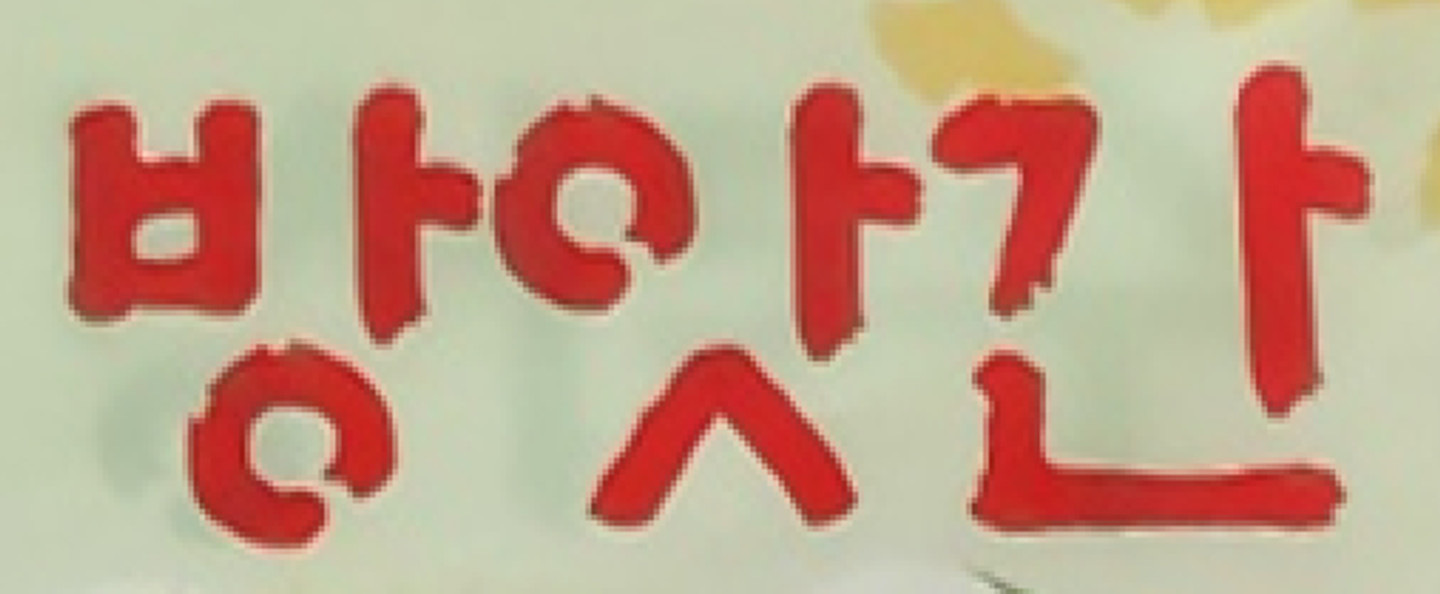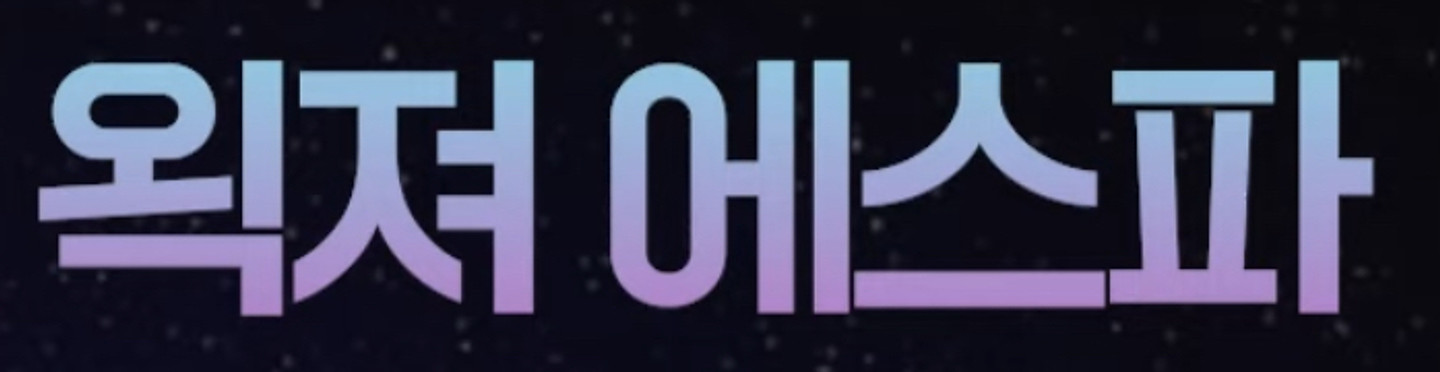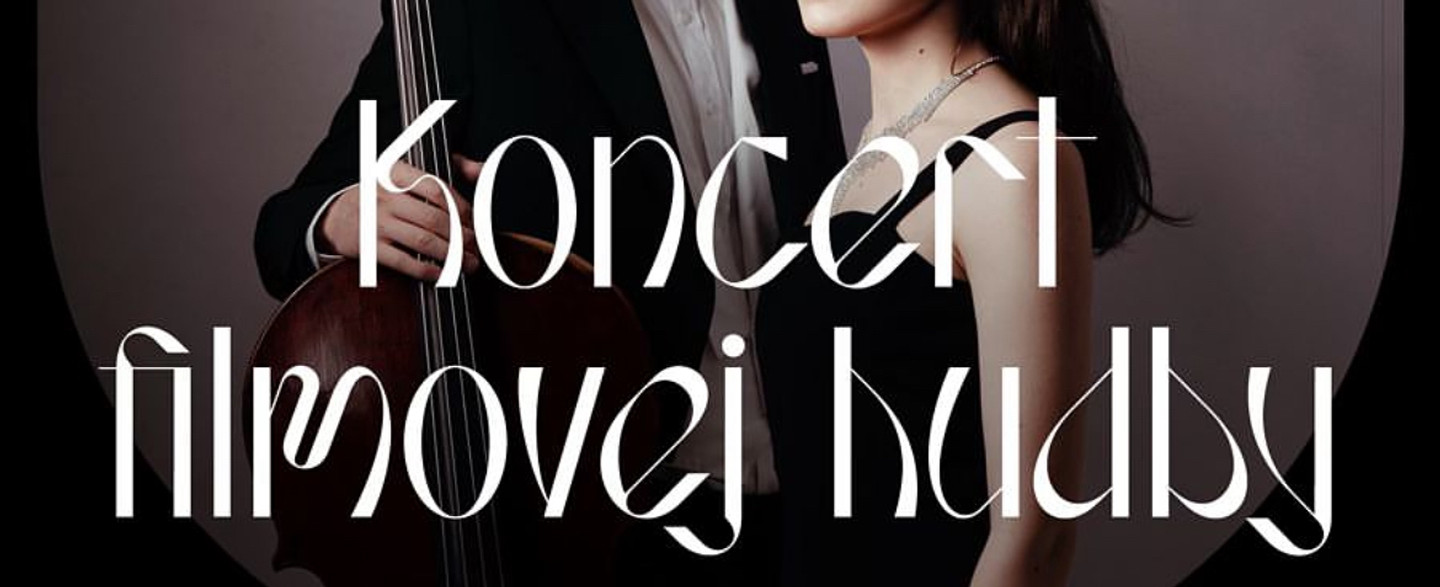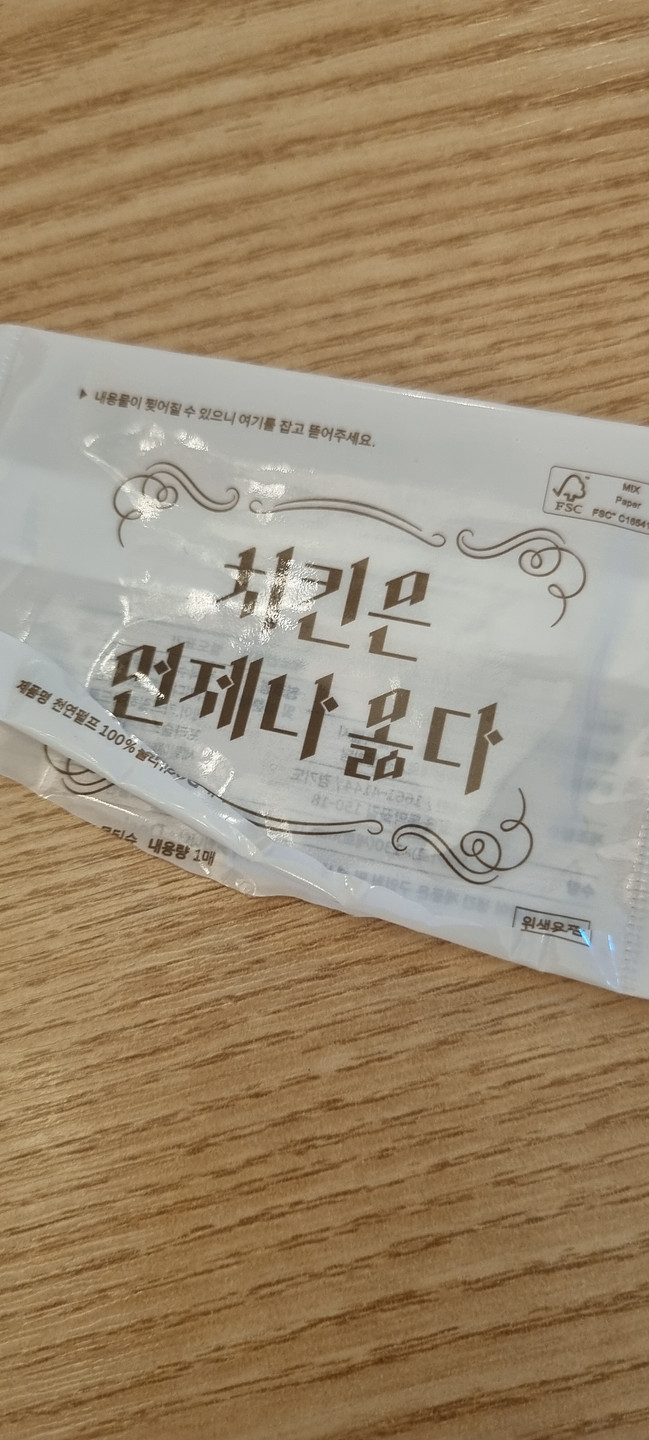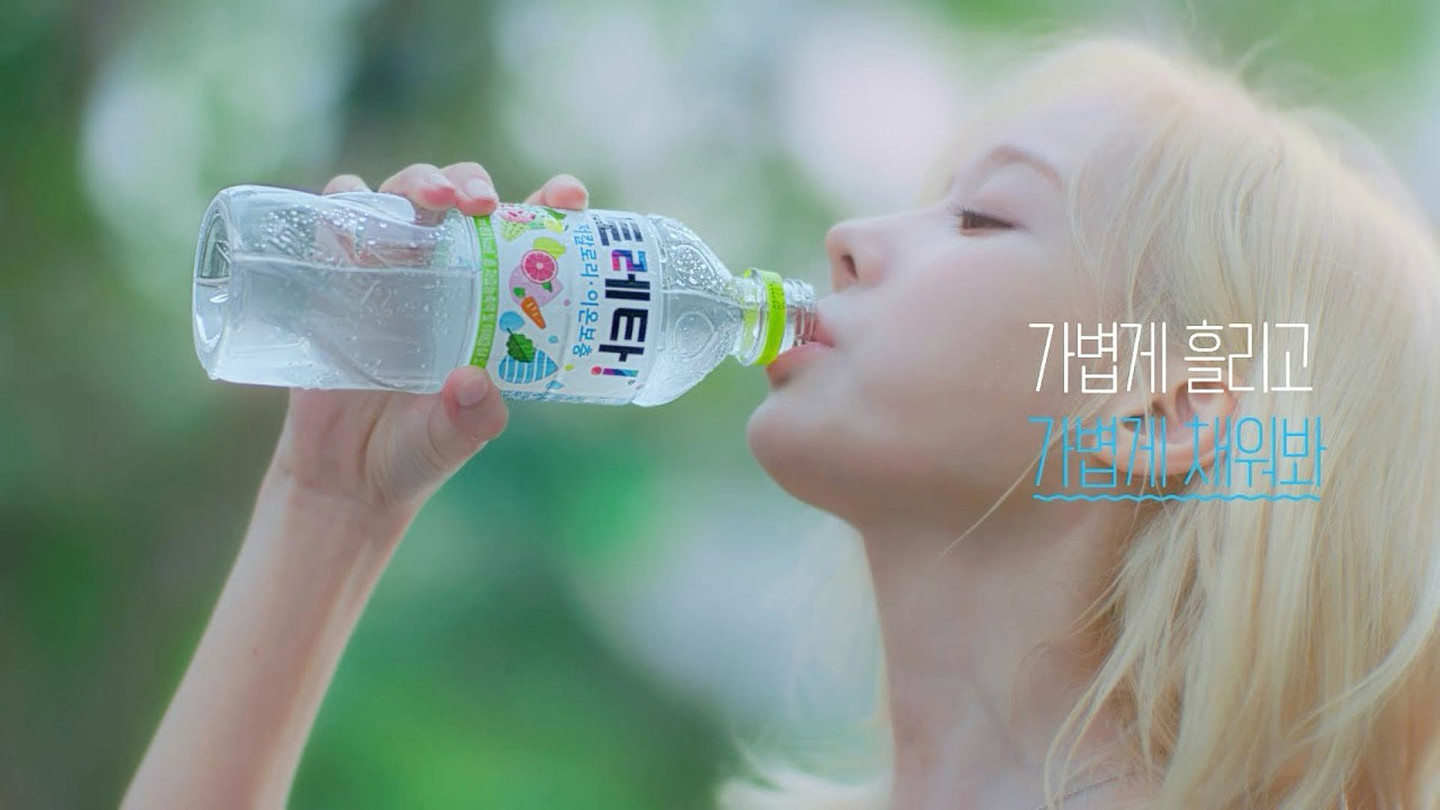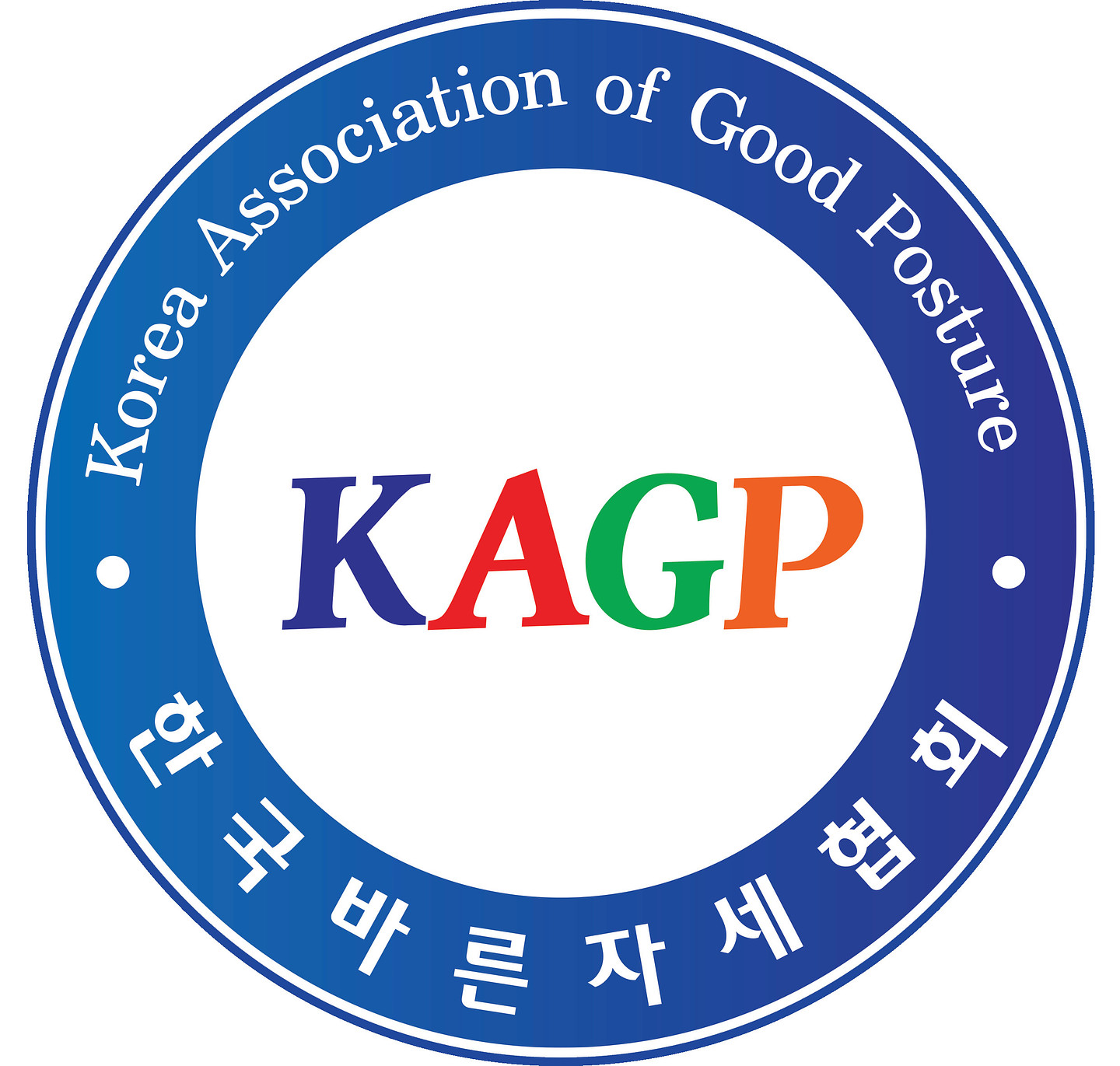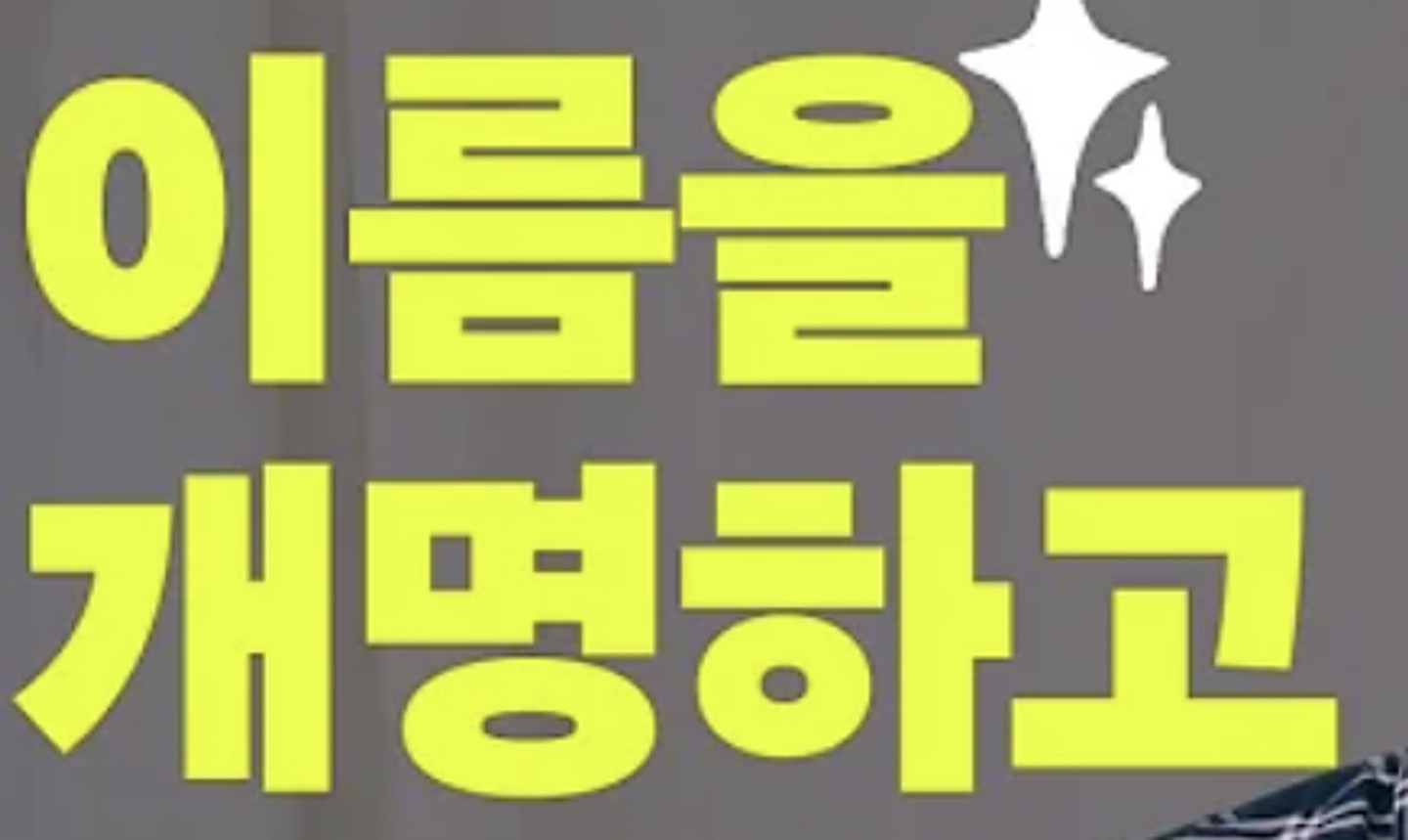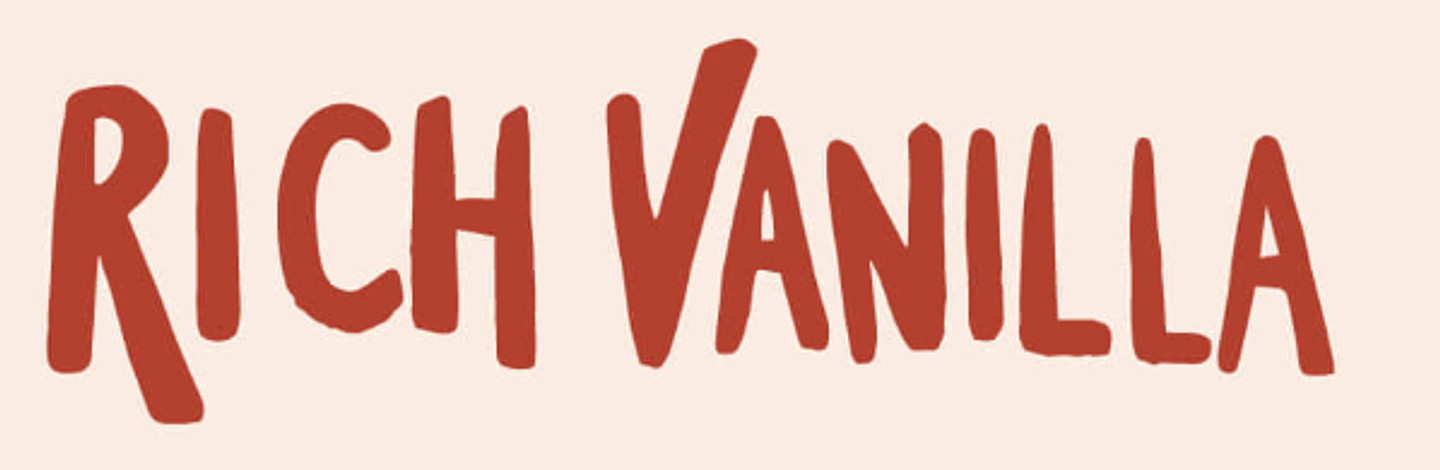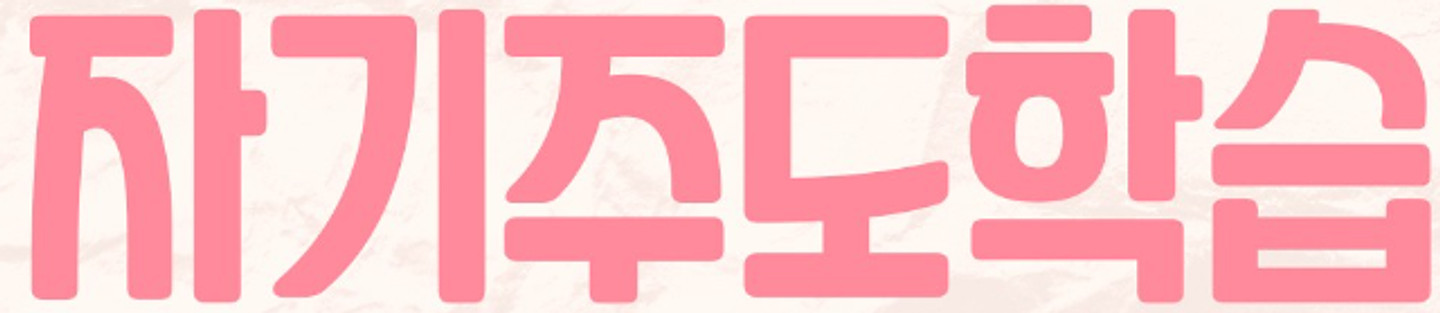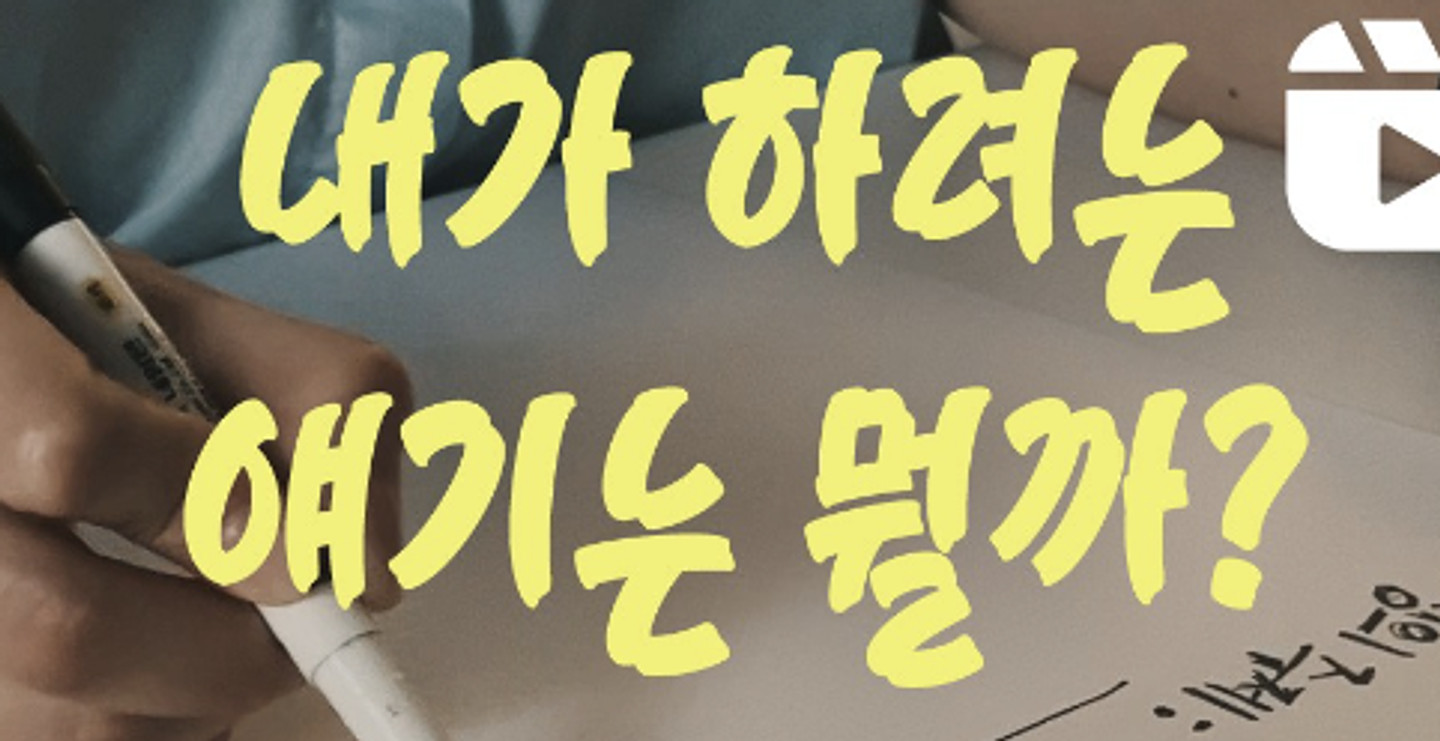
네. 오감을 자극하는 ~ 이 부분의 손글씨 같은 폰트 이름 알려주실 수 있을까요? 감사합니다.
타카슬라임카페 폰트명 부탁드립니다.
이거구 조금 왜곡잇습니다,,센세,, 찾아주십쇼ㅠㅜ
이 폰트좀 알려주세요
무슨 폰트인가요? ㅜㅜ 알고 싶습니다!!
무슨폰트인가여
예스24 티켓 뒷면 주의사항에 있느 글씨체 뭔가요?
'이제 c팀에서는' 글씨체 뭔가요?
이 폰트 아시는 분 계실까요? 알려주세요!
요 굴림이 어떤 폰트인지 궁금해요!!🤲 혹시 유료라면 비슷한 어도비/눈누에서 다운받을 수 잇는 폰트도 잇을까요🥺
이 썸네일 폰트 뭔가요?
<당연하게도 나는 너를> 폰트 질문합니다.
폰트 뭘까여
어떤 폰트인지 궁금해요!
폰트 알려주세여
The incredible machine 폰트가 궁금합니다
요코하마, 미나토구여자 이 굵은 폰트 이름이 뭘까요? 너무 궁금합니다.
너무찾고싶어요..
폰트궁금합니다 이거 굴림체인가요?? 일반 굴림체랑 조선굴림체랑 살짝 느낌이 달라서요
이거 어떤 폰트에요?
폰트 뭔가요? (파뿌리분들의 무인도 영상)
스포티비 썸네일인데, ‘캔자스스티 la다저스’ 폰트 뭘까요??
이 썸네일 폰트가 궁금해요! 아시는분 계신가요?
판권 폰트 질문이요
Hello baby Boy or Girl 글씨 폰트를 알고싶습니다!
사진 속 폰트 무슨 폰트인지 아시는 분 계실까요? 특이사항 : ㅁ 과 ㅍ 의 형태
영문 로고 폰트 혹시 무슨 폰트인지 아시는분...?!
이거 무슨 폰트인가용??ㅜㅜ
이 폰트 궁금합니다!! :)
폰트정보 궁금합니자
박보검의 칸타빌레 이 폰트 넘 독특하고 예쁜데 뭔지 아시는 분 있을까요 ?
이 폰트 너무 궁금해요
민음사 알베르 카뮈 디에센셜 일부분입니다
아이유 콘서트 가사 폰트인데 손글씨일 것 같긴한데 비슷한거라도 없을까요
자주 보이던데 무슨 폰트인지 궁금합니다.
이 영어폰트 무슨 폰트일까요?
만화등에서 쓰이는 폰트 같은데 이름을 모르겠어요
무슨 폰트일까요ㅜㅜ?
무슨 폰트인지 알고 싶습니다
용감한 형사들에 나온 폰트인데 뭔지 궁금합니다 아시는분 있으신가요??
이거 어떤거임?
이거 폰트 어떤건지 당장 말해!!!!
해당 사진 속 폰트 무슨 폰트일까요?
귀여우면서도 가독성이 높다
아이브 자컨 폰트입니다 무슨 폰트일까요?
안녕하세요~ 요건 글씨체가 뭘까요??
무슨폰트인가요
이거 무슨 폰트인가요....
식스센스 2화에 나온 자막인데, 이 폰트 뭘까요…? 답변 미리 감사합니다.
이거 무슨 폰트에요ㅠㅠㅜ
스티커에 많이 쓰이는 이 말투.. 꼭 알고싶습니다ㅜㅜ 알려 주실분 미리 감사드립니다!!
고수님들 알려주시면 너무너무 감사드리겠습니다.. 미리 감사드린다는 말 드려요!!